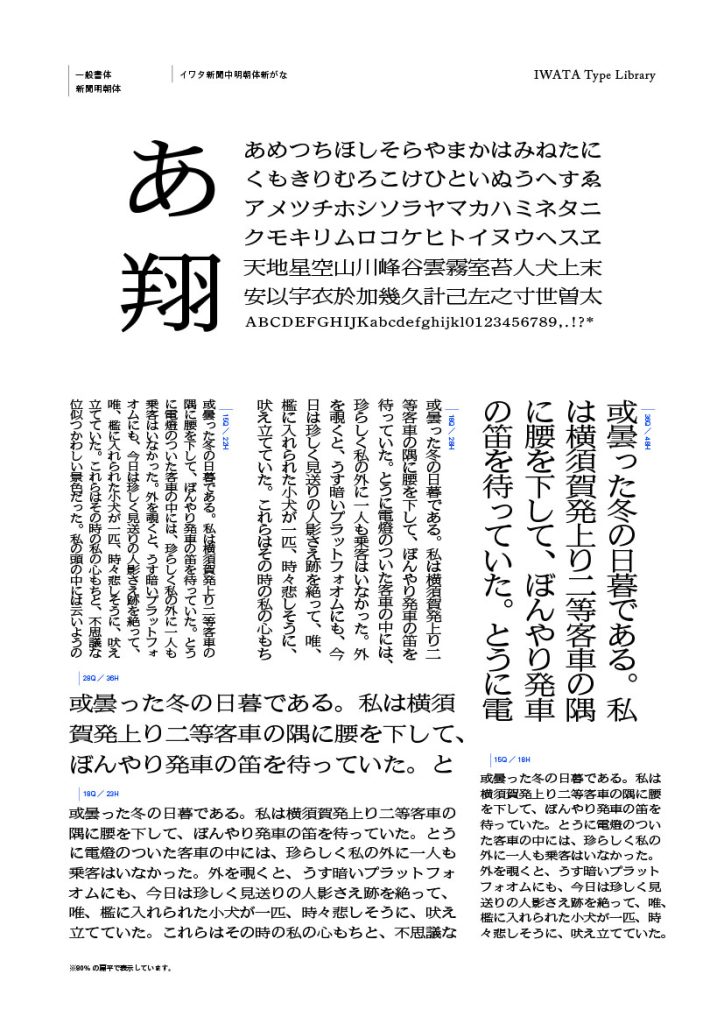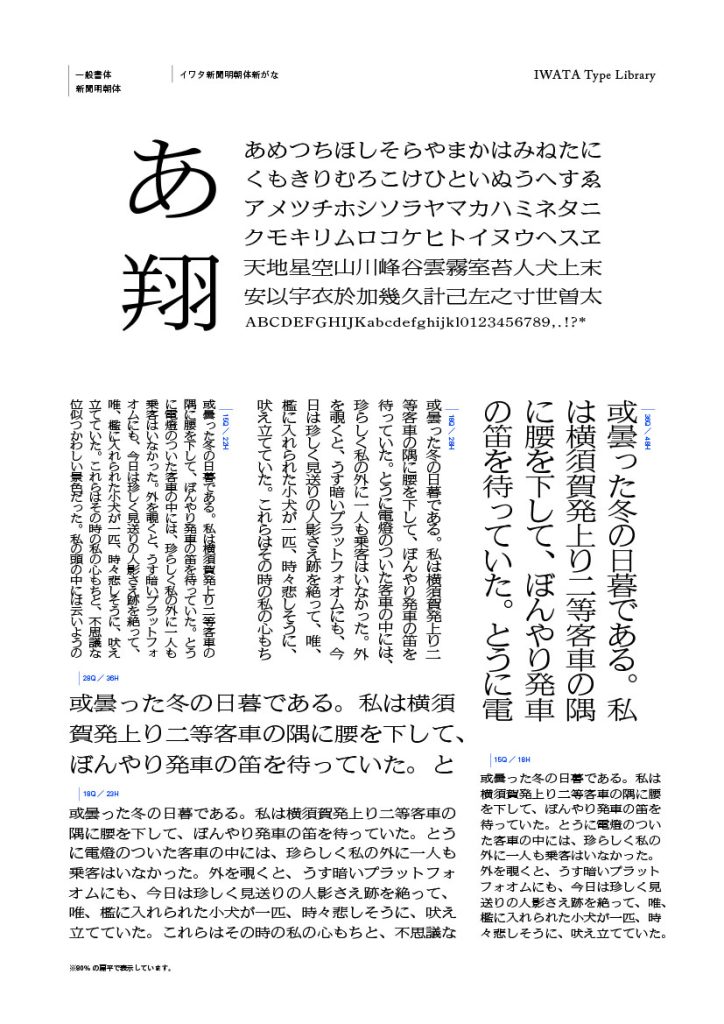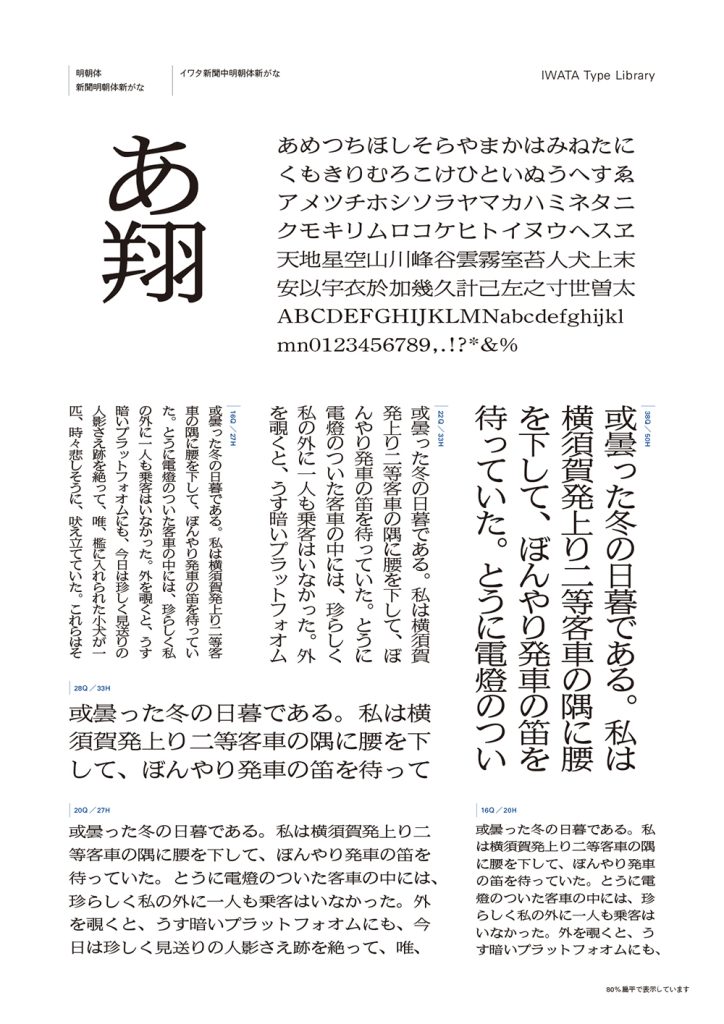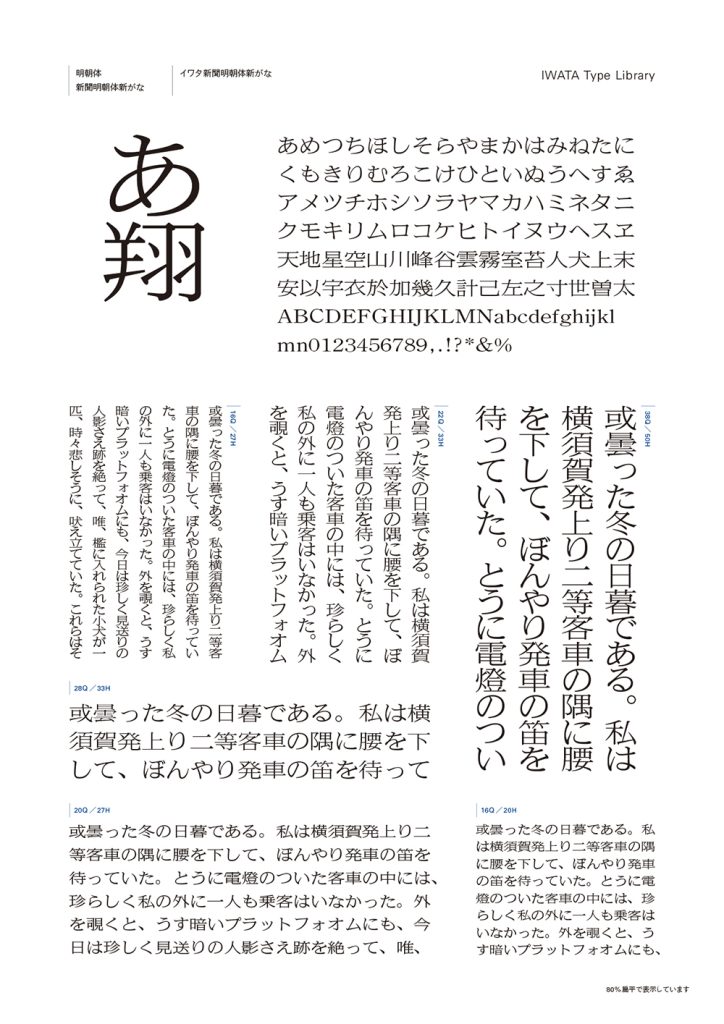
「イワタ新聞明朝体」の仮名を現代風にアレンジした書体です。80% 扁平に変形使用することを想定して設計されています。
「イワタ新聞明朝体」について
昭和16 年に岩田母型製造所が開発した新聞本文用書体「岩田新聞明朝体」を源流とし、活字由来の字形を再現した歴史ある新聞明朝体で、多くの新聞社に採用されてきました。いわゆる新聞書体の特徴を色濃く残した佇まいが魅力で、広告や装丁などにも幅広く活用されています。
書体デザインのポイント
新聞明朝体の雰囲気を活かしながら、よりモダンさや明瞭さを感じられる書体です。
※「イワタ新聞明朝体標準かな」と「イワタ新聞明朝体新がな」を比較しています(扁平率はどちらも80%)